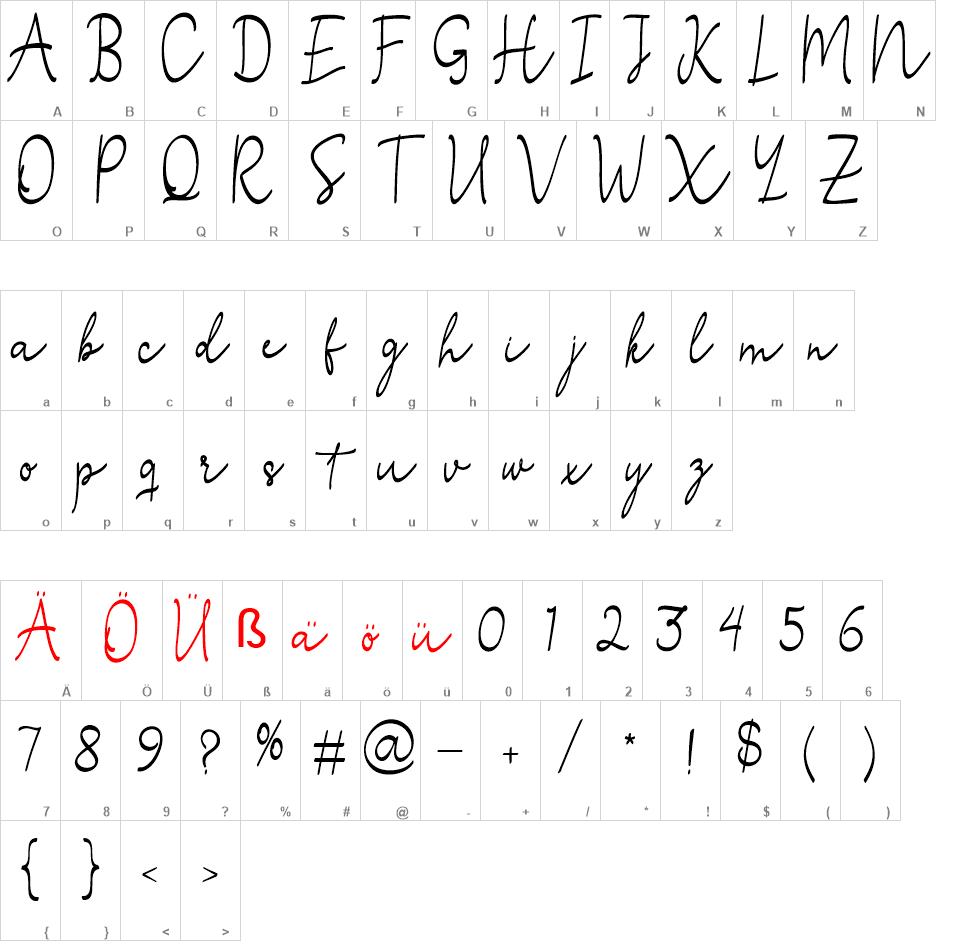
Stefian Script
Stefian Script ist eine moderne Kalligraphie Schrift mit
der aktuelle Handschrift Stil, ist diese Schrift perfekt für das Branding,
Hochzeit Einladungen, Zeitschriften, Tassen, Visitenkarten, Zitate, Plakate und
Stefian Script ist mit 380 Glyphen ausgestattet. und
durch viele dieser Glyphen wird es möglich sein, die Buchstaben zu wählen
nach Ihren Vorlieben, viele Variationen und Optionen für jeden Buchstaben,
so können Sie auf Ihre Design-Entscheidungen anpassen.